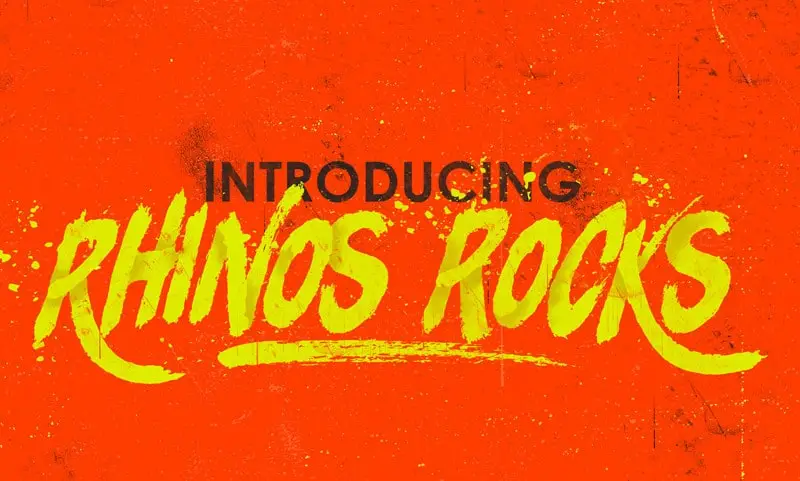
Rhinos Rocks Brush Font – Fonte Grátis
Rhinos Rocks Brush Font
Esta font Rhinos Rocks Brush é uma explosão de energia, com traços rápidos e ângulos aguçados. Perfeita para mensagens vibrantes e poderosas. É um recurso incrível para criar logotipos, cartões de nome, citações escritas a mão, embalagens de produtos, materiais de merchandising, cartões de felicitação e até mesmo design para camisas ou outros produtos de moda. Além disso, é ótima para transformar qualquer ideia em uma expressão vibrante que transborda confiança e atitude. Ideal tanto para a criação de marcas memoráveis quanto para aqueles que valorizam um toque único e criativo em seus projetos.